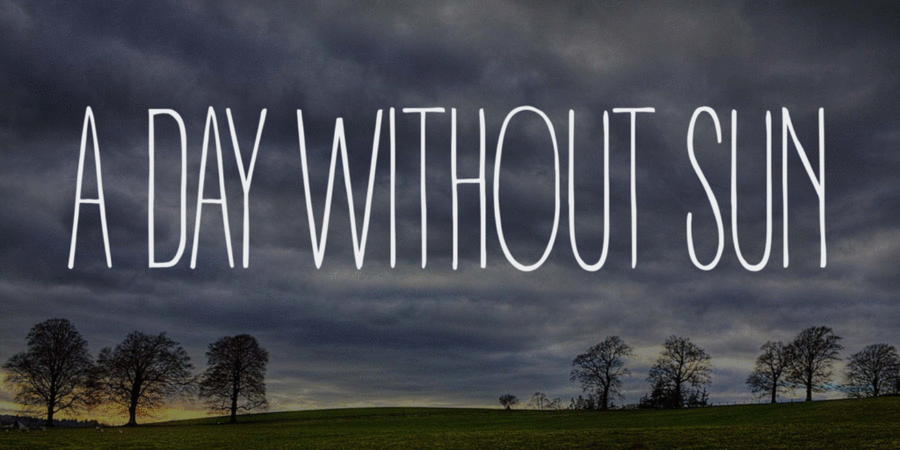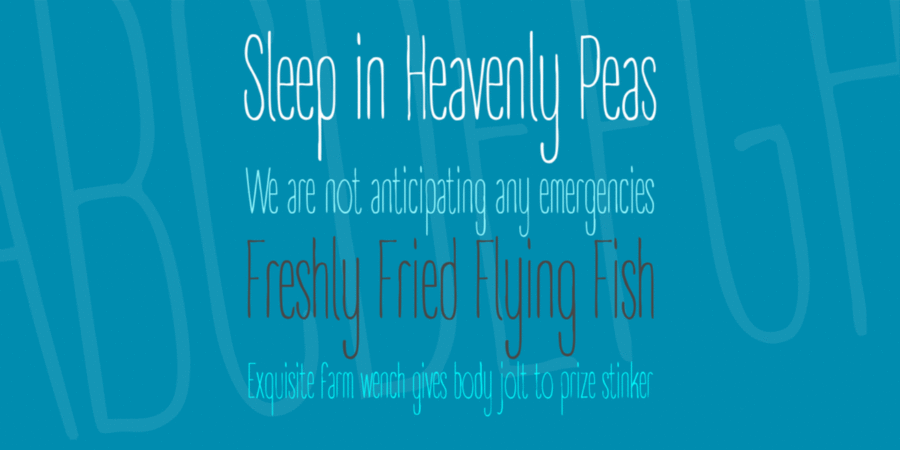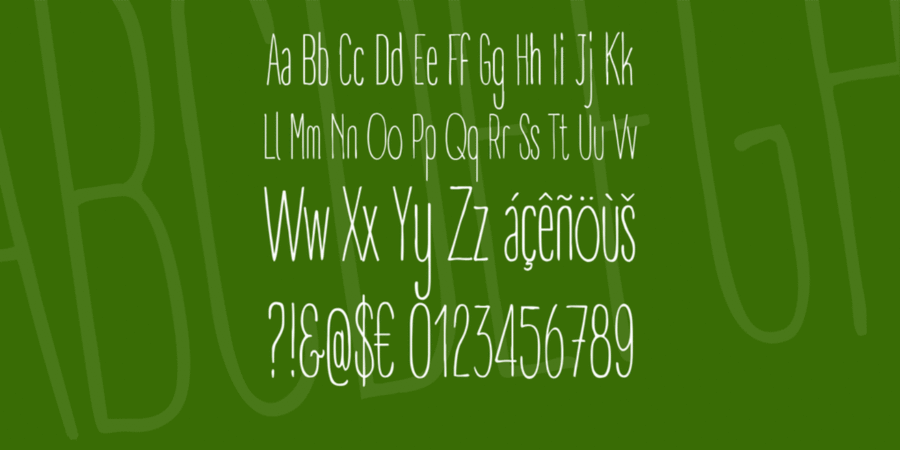
Шрифтова пара з Excentra Pro Regular (1 з 4)Опис шрифта Day Without SunДень без солнца – неформальный рукописный хипстерский шрифт, часть шрифтового семейства Pro Panforte. Кроме латиницы, содержит кириллический и греческий наборы символов, а также капитель, лигатуры и минускульные цифры. Шрифт разработан Деборой Манетти в 2014 году и выпущен фирмой Zetafonts. A day without sun by Zetafonts –http://www.zetafonts.com/collection/188
Асоціації з сімейством шрифтів Day Without SunОсобистість і характер гарнітури:
оригінальний, свіжий, високий, стрункий, рівний, лаконічний, сучасний, модний, живий, довірчий, худий, тонкий, легкий, характерний, повітряний, рукотворний, затишний, привітний, доброзичливий, приємний, зелений, природний, інтимний, крихкий, весняний, кустарний, саморобний, сімейний, домашній, органічний, осінній, сумний, натуральний, вернакулярний, лісовий